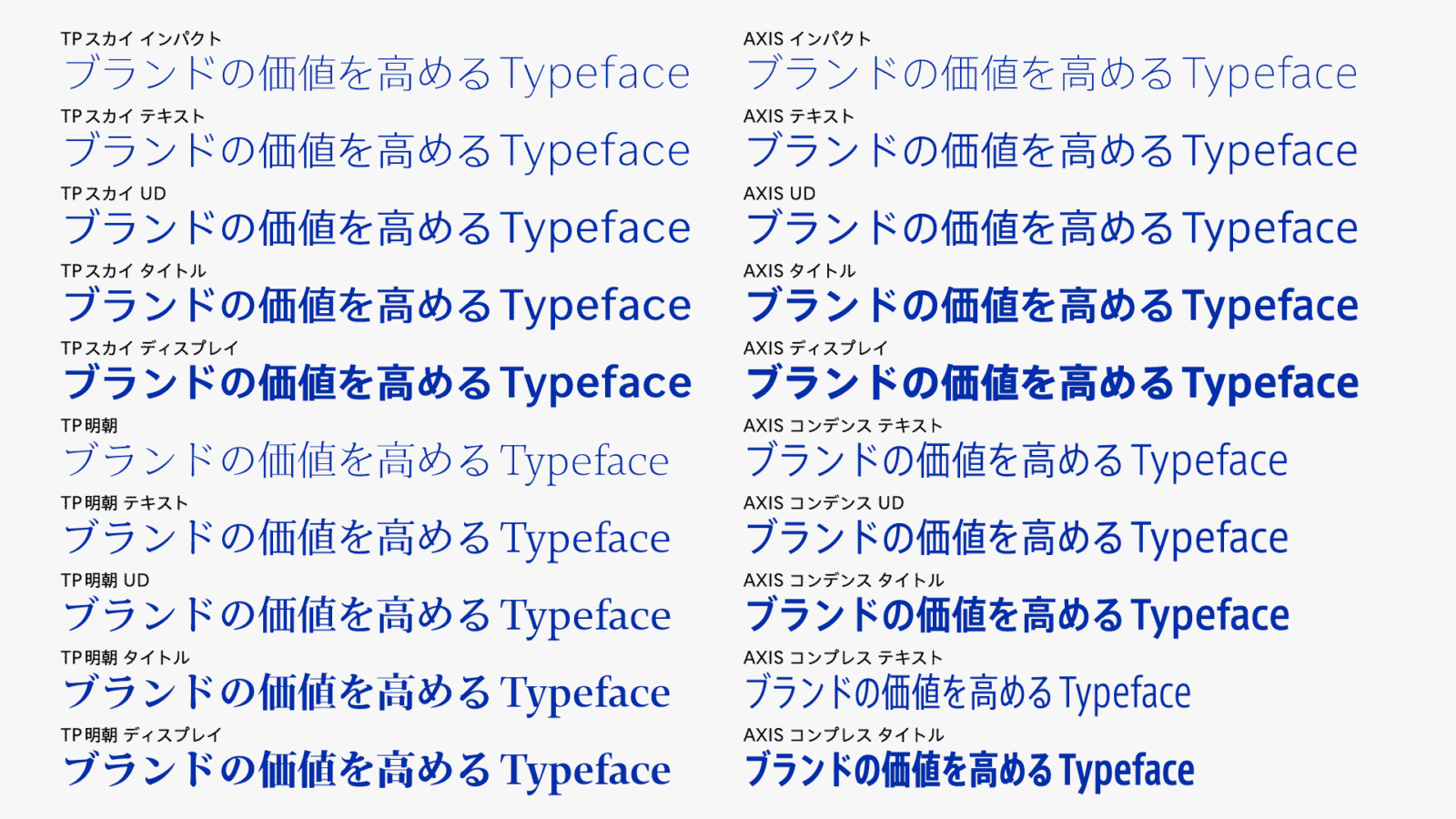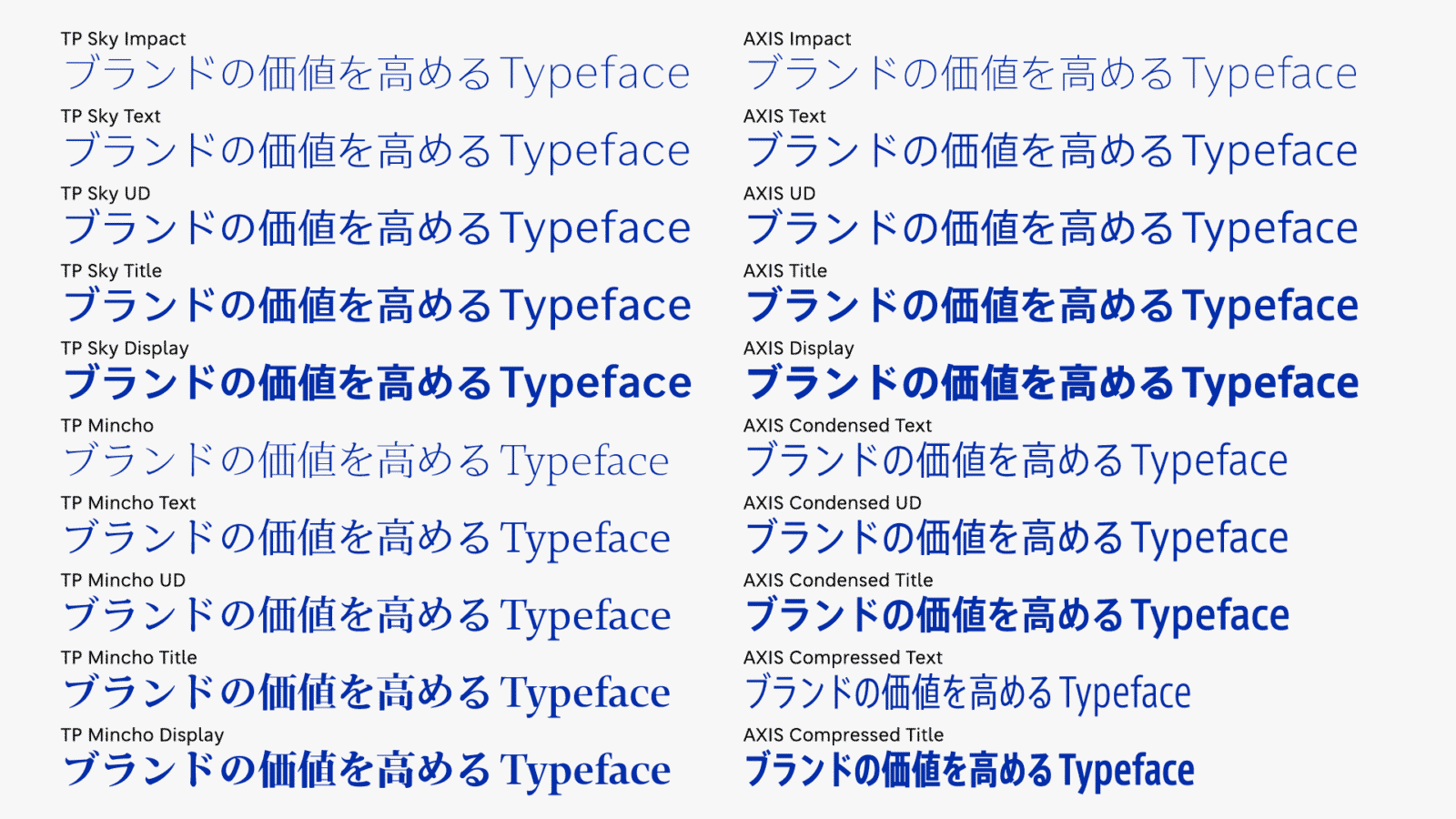
会社の「声」となるコーポレートフォントを
企業の「声」を担うコーポレートフォント
会社には、伝えたいことがたくさんあります。どんな考えでモノをつくっているのか。どうやって、社会の役にたっていきたいのか。これから何を目標に歩んでゆくのか。企業を人にたとえるなら、その言葉に表情を与えるコーポレートフォントは、「声」のようなものだと言えます。企業とユーザーのあらゆる接点において、自社の声にふさわしいフォントを用いることで、顧客から見た企業のイメージに一貫性を与え、信頼性という貴重な資産を着実に形成することができます。コーポレートフォントは、企業のブランド価値を高めるだけでなく、アイデンティティを確立することで、インターナルブランディングの強化にも繋がります。
4つを選ぶ組み合わせは、4,845通り。
タイププロジェクトでは、横組みに特化したデザインやUD適性、デジタル画面での表示適性、表示速度を考慮した設計など、多様化しているメディアに対応したフォントを開発しています。また、他社の欧文フォントに合わせてウエイトや字幅などを調整する技術を開発し、国内外の大手電機メーカーや自動車メーカーなどにコーポレートフォントを提供しています。法人プランで選べるフォントは、清新な印象を与える「インパクト」、本文に最適な「テキスト」、小さな文字でも可読性の高い「UD」、見出しや大きなサイズで効果的な「タイトル」と「ディスプレイ」。3つのフォントファミリーの20フォントとなっています。ビジネスに合わせたフォントをご指定ください。
法人プランでは、主要フォントであるAXIS Font、TP明朝、TPスカイのフォントファミリーから、一般販売を行っていないラインナップを用意いたしました。